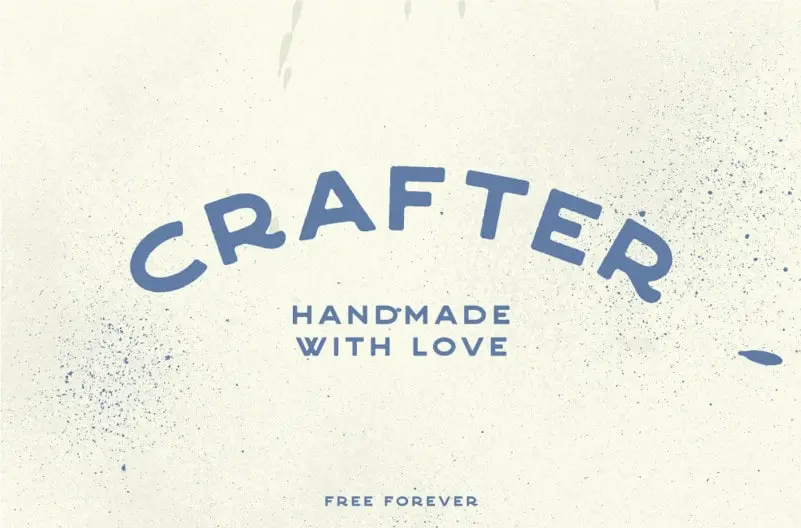
Crafter Vintage Font – Download Grátis
A fonte Crafter Vintage Font é uma família sans-serif que carrega um toque elegante e moderno, perfeitamente adaptada para projetos vintage. Ela foi criada pelo designer 1871 Project, inspirado nas antigas marcas metálicas e pinturas de sinais. Esta fonte não só oferece um visual atraente, mas também serve como uma ferramenta versátil que pode ser usada em logomarcas, camisetas customizadas, panfletos, redes sociais ou praticamente qualquer projeto onde você precise de um toque vintage e moderno. Sem dúvidas, é perfeita para seu próximo trabalho de design. Não se esqueça de que embora seja uma fonte elegante, ela não deve ser usada em parágrafos extensos por conta do seu tamanho reduzido em algumas situações.
Designer: Tommy Soft